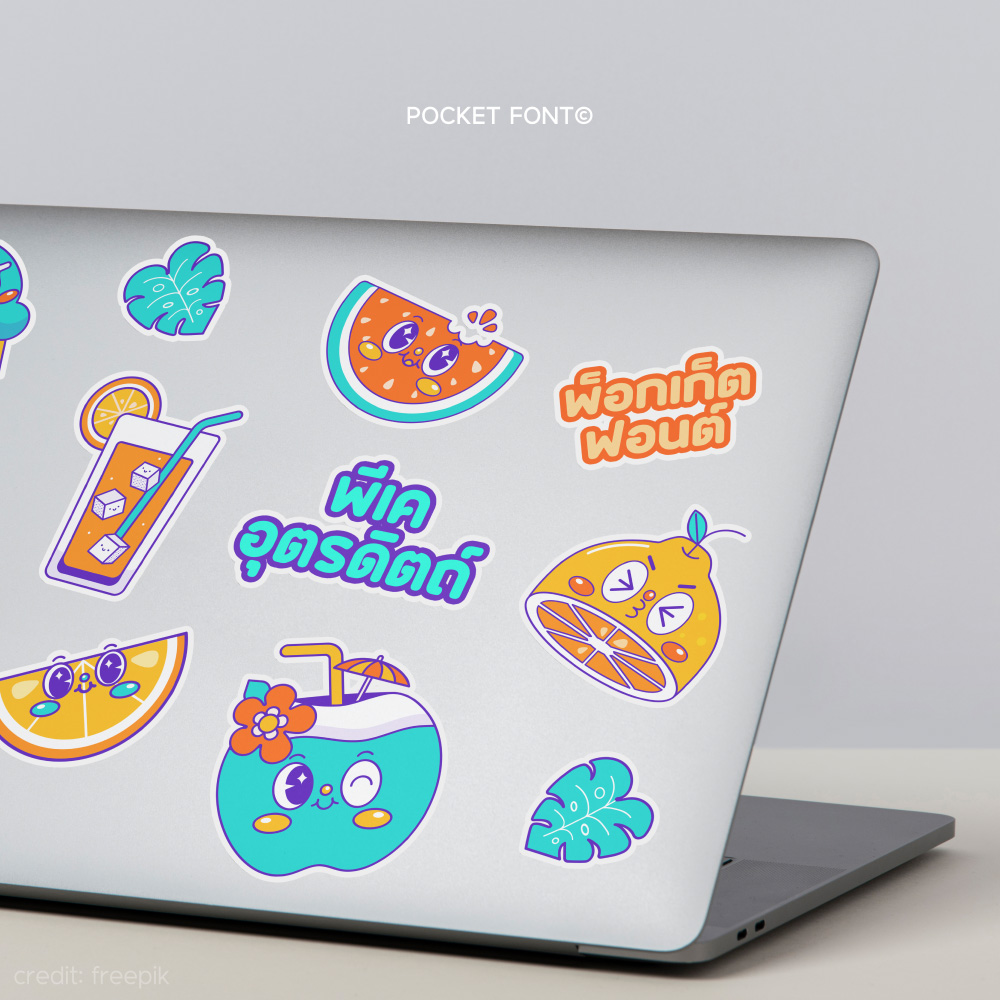
พีเค อุตรดิตถ์ | PK Uttaradit
ชื่อฟอนต์ พีเค อุตรดิตถ์ | PK Uttaradit
พีเค อุตรดิตถ์ เป็นฟอนต์ที่ดูเรียบง่าย สะอาดตา และจะดูน่ารัก เป็นกันเองมากขึ้นเมื่อปรับเป็นปลายมน มี 5 น้ำหนัก และเป็น Variable font นอกจากนั้นยังสามารถ ปรับความโค้งมนของปลายเส้นได้ถึง 3 ระดับ Fixed (Edge, Round corner, Rounded) และ 12 ระดับ Variable